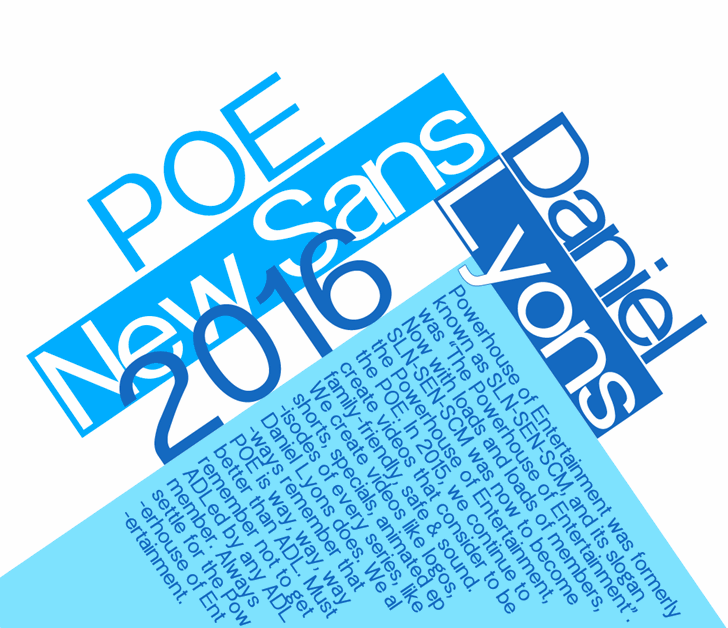
POE Sans New Font Family – Download Grátis
A POE Sans New Font Family é uma nova versão do POE Sans Pro font, inspirada no famoso Times New Roman de 1931 criado por Stanley Morison. Esta novidade foi desenvolvida pelo designer Hamilton no ano de 2016 e traz quatro estilos para você escolher. Este novo projeto é uma opção fresca e moderna para quem procura fontes sem sercuris, ideal para textos informativos e design gráfico. Com a POE Sans New Font Family, sua próxima obra pode estar repleta de estilo e elegância.